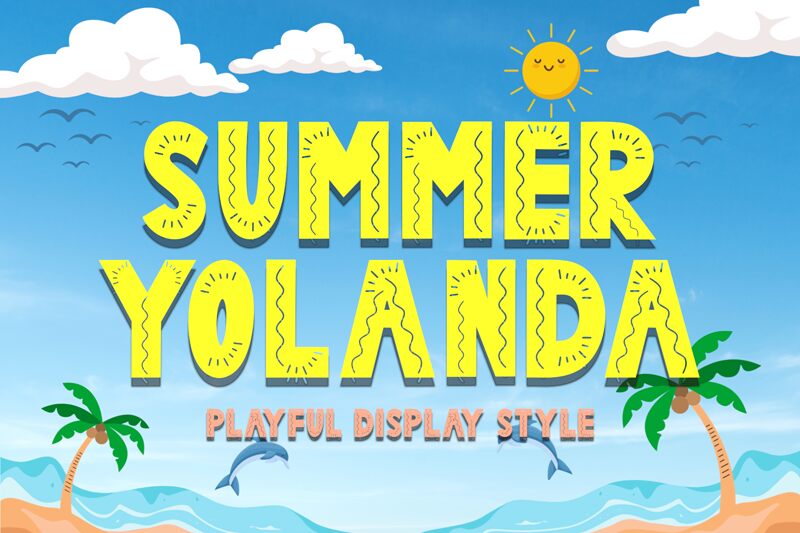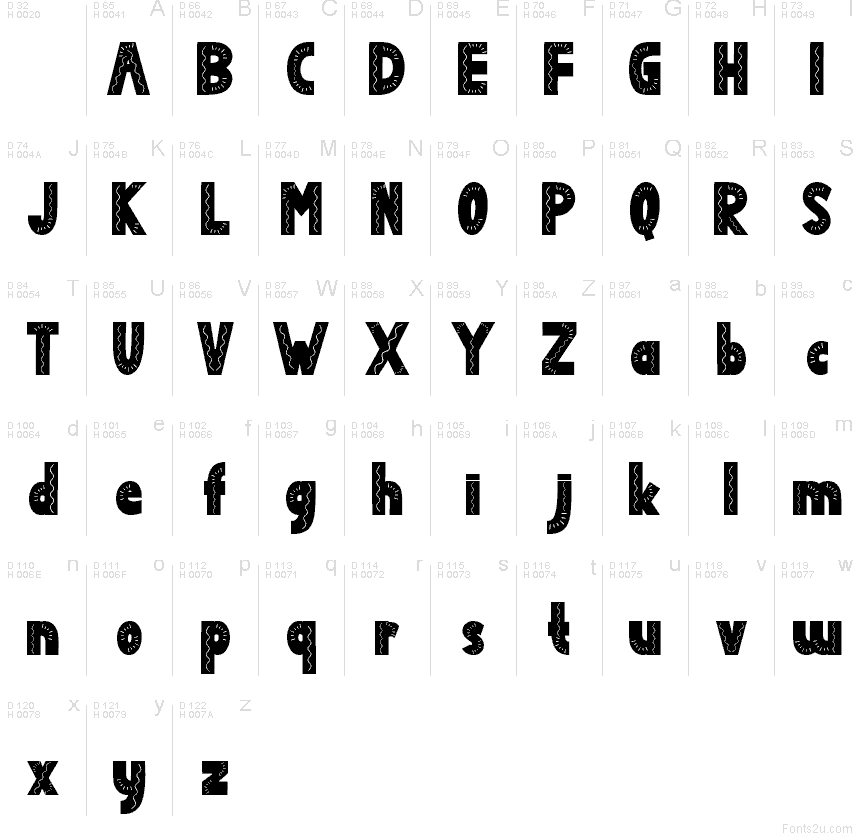
Summer Yolanda
Summer Yolanda de Yoga Letter es una tipografía decorativa tipo display, caracterizada por sus letras redondeadas de gran formato y sutiles destellos solares integrados en trazos seleccionados. El diseño de la «u» incorpora además líneas onduladas internas, aportando un aire artesanal y playero que evoca la calidez del verano sin llegar a ser recargado.
Summer Yolanda es ideal para carteles de eventos estivales, folletos de resorts, branding vacacional, menús, rótulos de tiendas y gráficos en redes sociales que busquen un toque estacional. Gracias a sus detalles de sol integrados y su estética fluida, esta fuente gratuita cumple una doble función: sirve como titular y como elemento decorativo por sí misma.